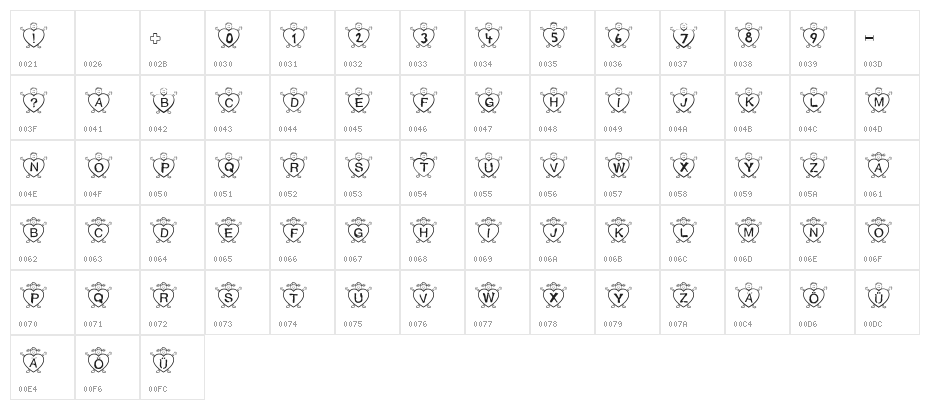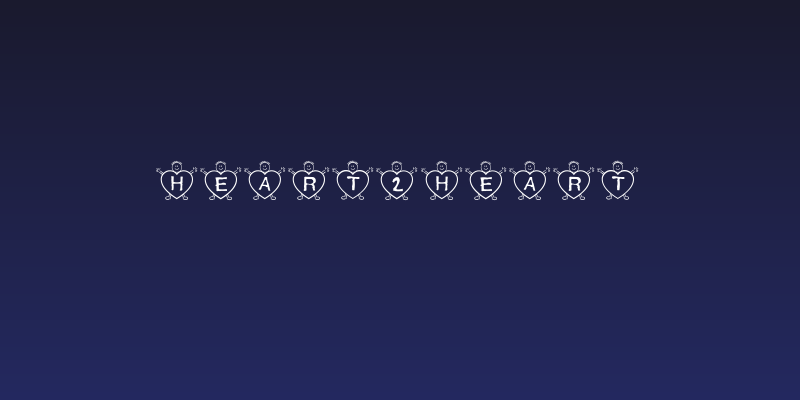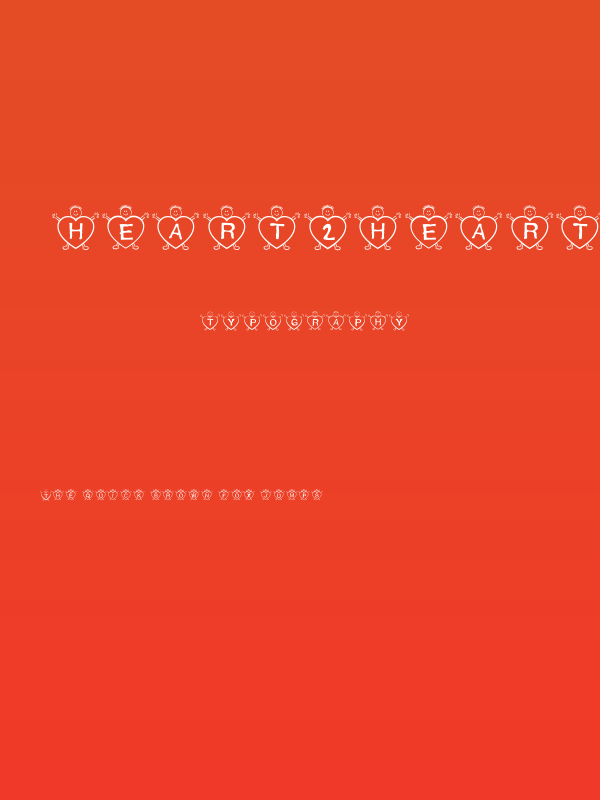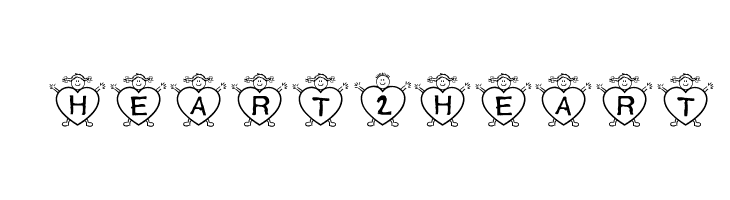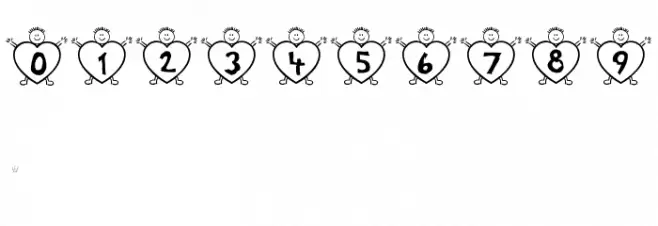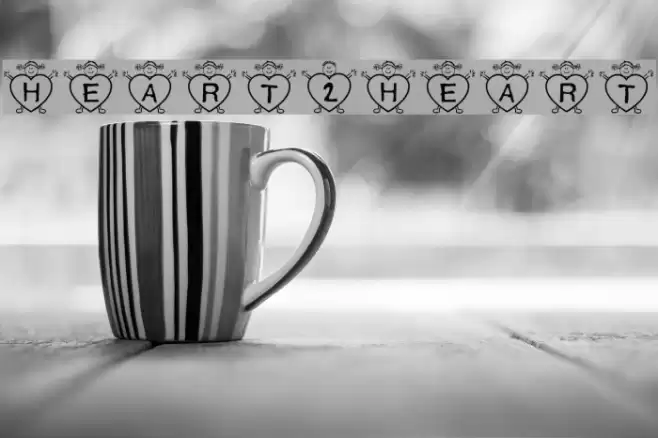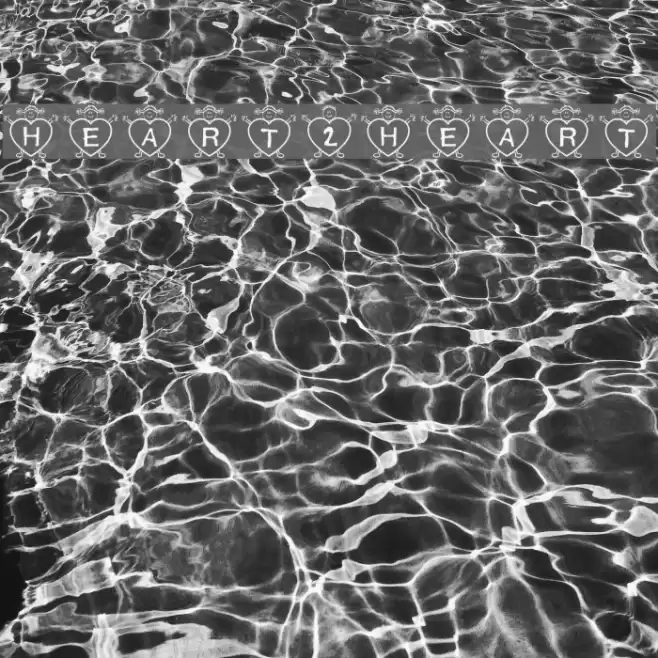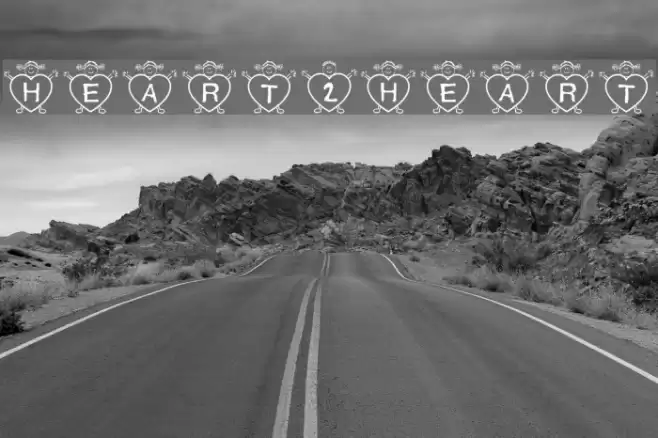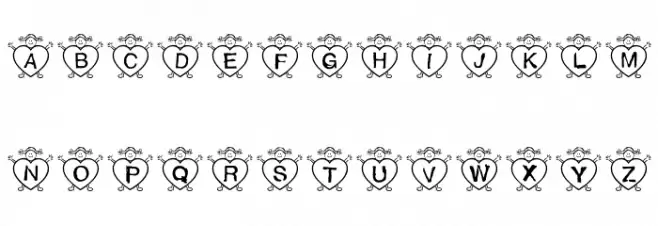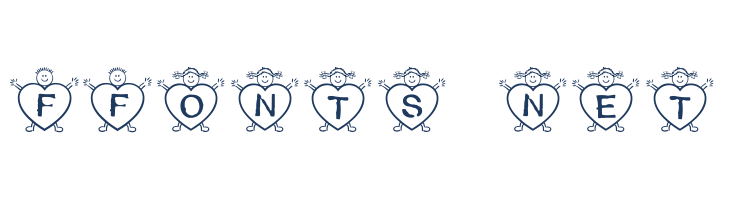
*heart2heart* Font
Esta fuente incluye 82 caracteres. Haz clic en cualquier carácter para ver los detalles.
| Estilo general | Playful |
| Caso de uso | Logos, Headlines, Decorative text |
| Proyectos propuestos | Ideal for children's books, playful greeting cards, party invitations, and whimsical branding materials. |